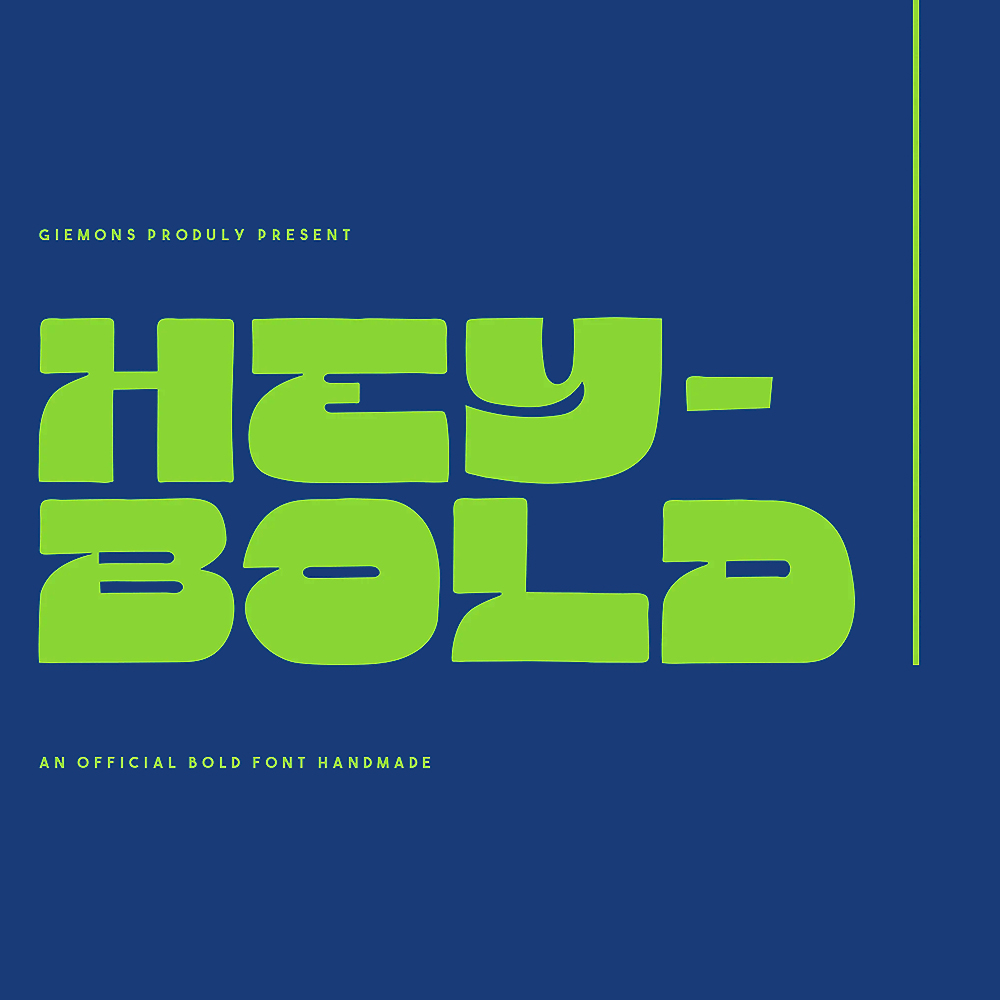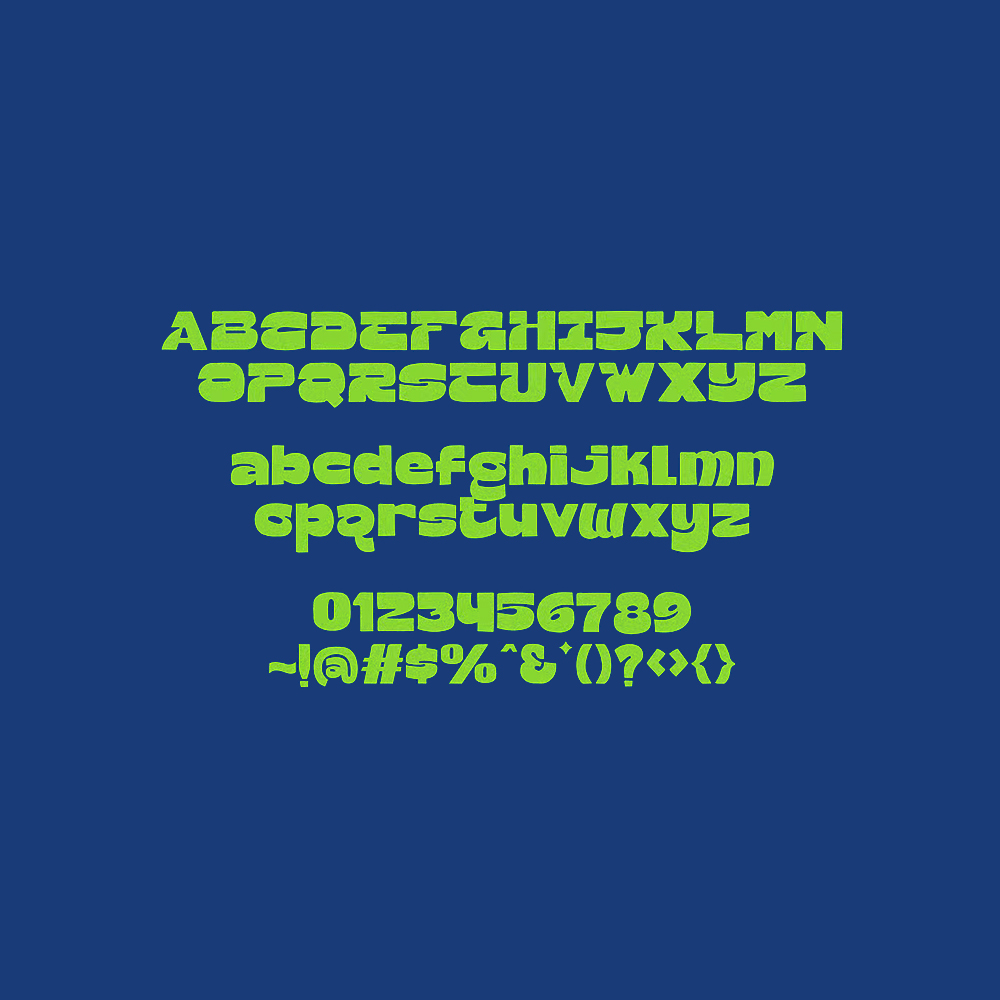
فونت پرمیوم و انگلیسی Hey Bold Font یک فونت مدرن و جسورانه است. خطوط خشن و دستساز آن، حس طبیعی بودن را القا میکنند و برای لوگوها،…
فونت پرمیوم و انگلیسی Hey Bold Font یک فونت مدرن و جسورانه است. خطوط خشن و دستساز آن، حس طبیعی بودن را القا میکنند و برای لوگوها، تیترها، پوسترها و موارد دیگر با کمی درخشش، عالی هستند.
مزایای استفاده از فونت لاتین Hey Bold چیست؟